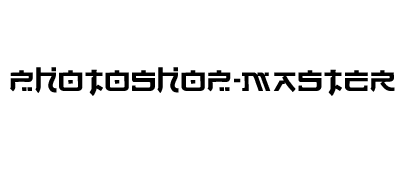
+1, спасибо большое, жаль русской версии нет
Классный шрифт
ахахаха... теперь любое слово будет на китайском))))
От поклонников из Владивостока РЕСПЕКТ!!!!! Отличный шрифт для оформления..... ну скажем наших японских авто.